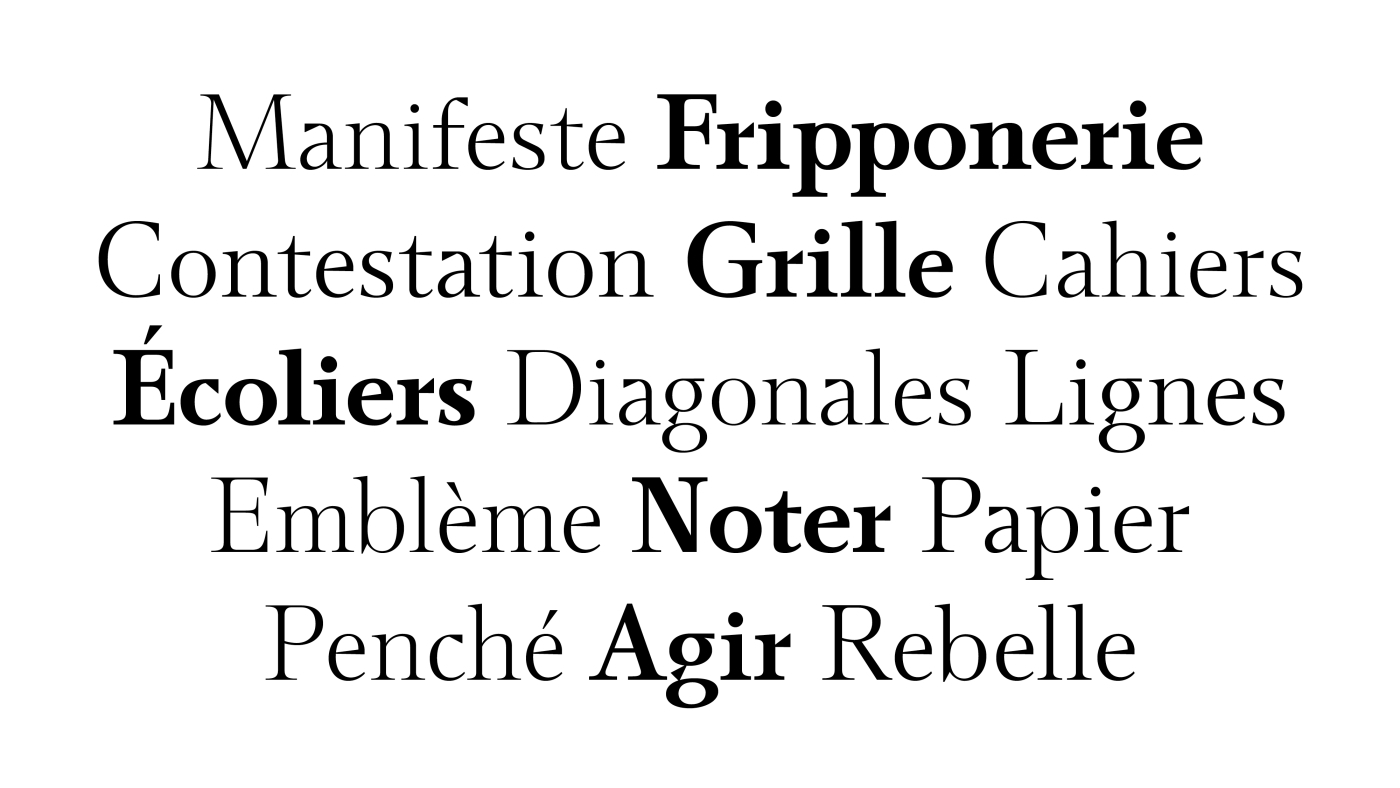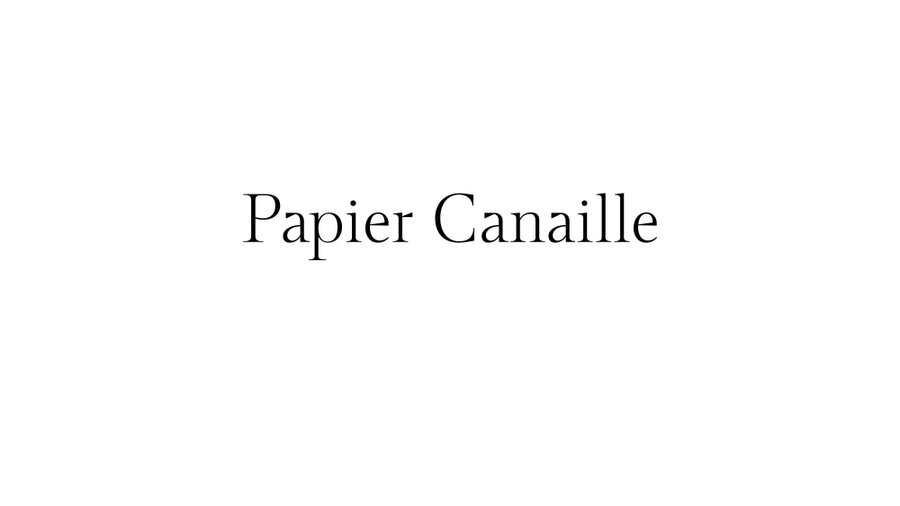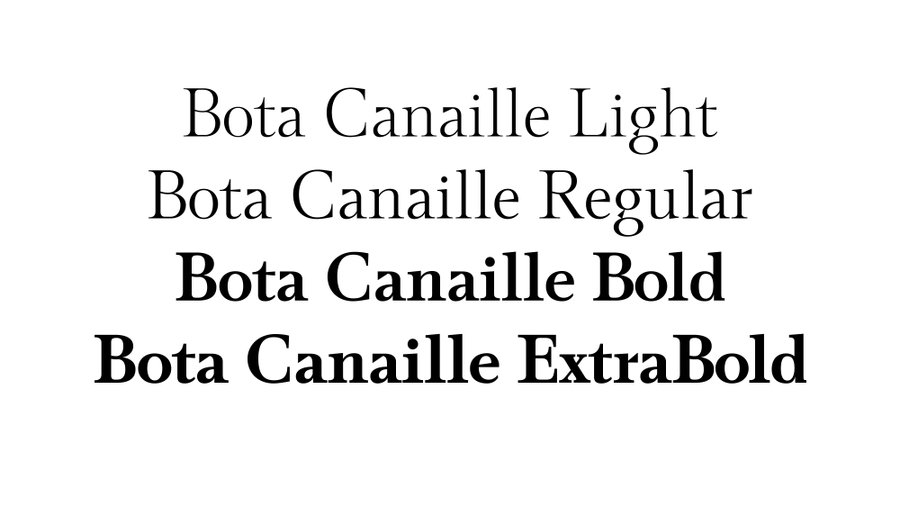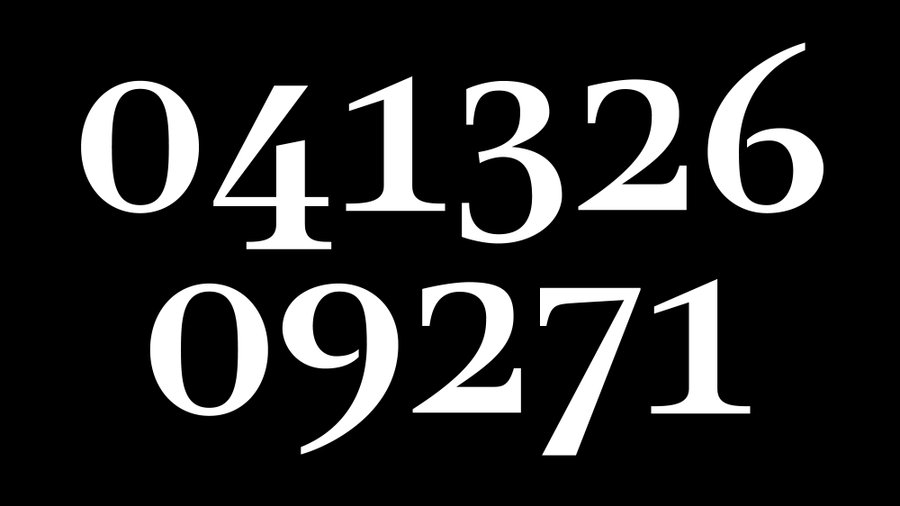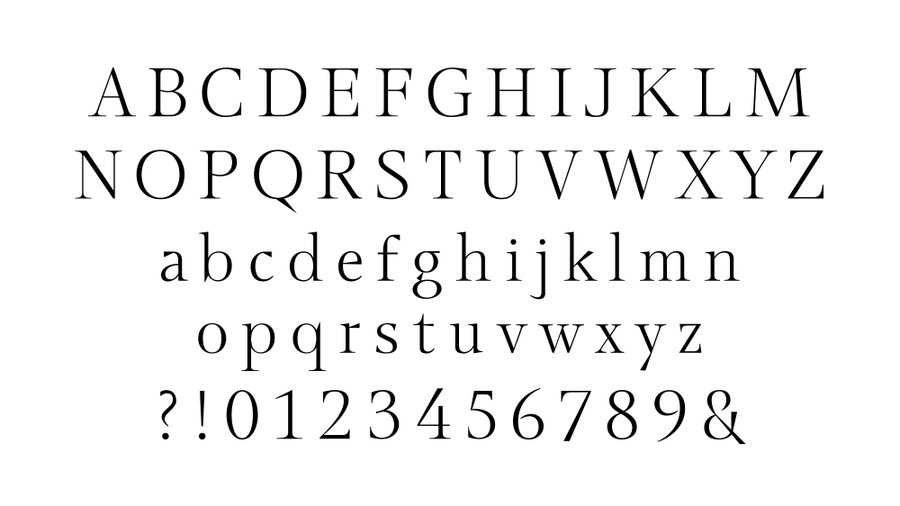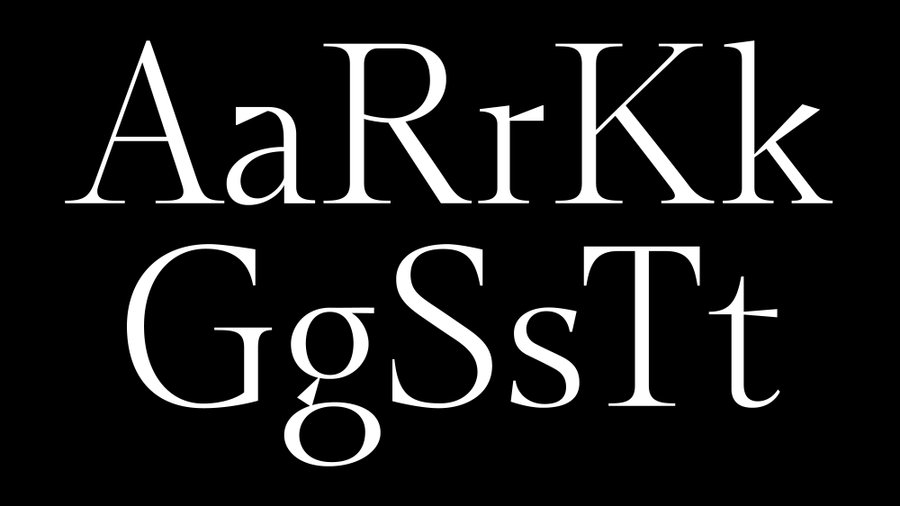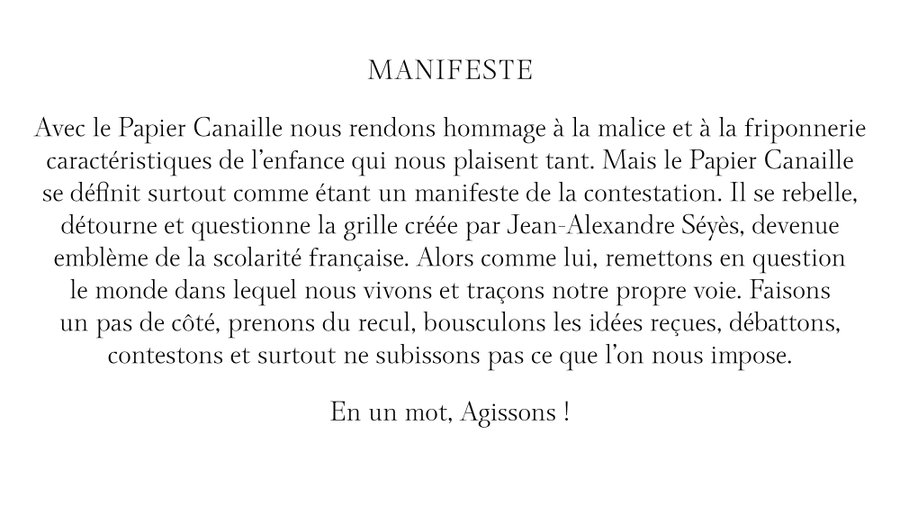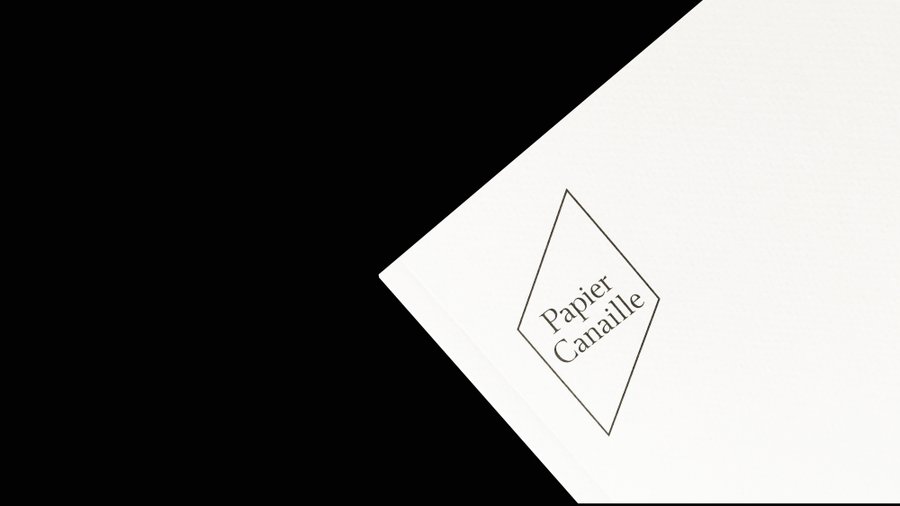
Bota Canaille, typographie sur-mesure
Papier Canaille est une marque de papeterie française qui édite
des cahiers inspirés de ceux des écolièrs.
En revanche les lignes ne sont plus droites !
La marque se dote de la Bota Canaille une typographie sur-mesure
et réalisée d'après la typographie Bota dessinée par mes soins.
Elle est utilisée à la fois pour le logotype, sur et dans les cahiers,
sur la papeterie de la marque ainsi que sur le site web.
Création d'une famille typographique de marque.
4 graisses du Light à l'Extra Bold
Papier Canaille
Dessinateur de caractères